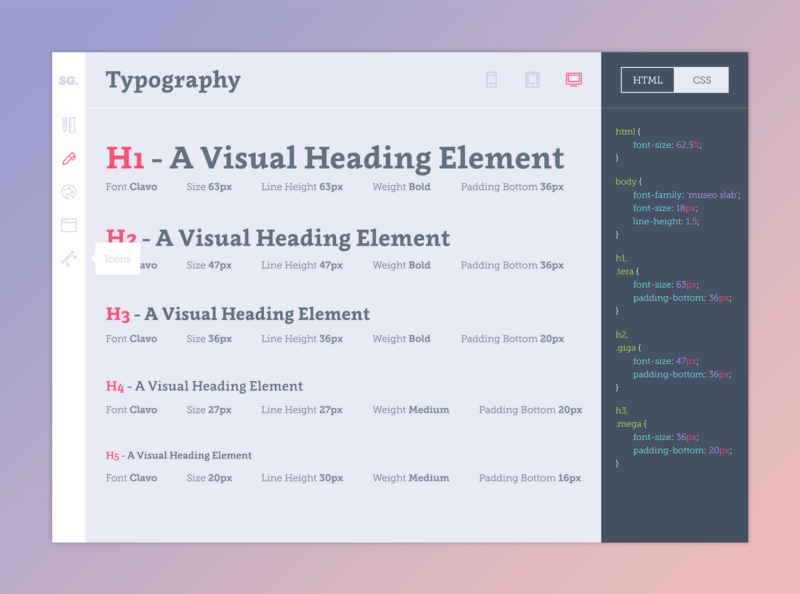
Будем считать, что художественный вкус дизайнера в рамках данной статьи не обсуждается. Я — всего лишь программист, технарь, придаток машины, да что же я понимаю в Прекрасном? Разве могу я указывать дизайнеру как Творить? Конечно же нет.
Долгое время на веб-страницах в Интернете можно было использовать только ограниченное количество шрифтов, которые встроены в операционную систему, так называемые web-safe-шрифты. Но несколько лет назад появилась директива @font-face, позволяющая встроить в страницу любой шрифт. Конечно же, дизайнеры обрадовались этой новости. Ещё бы, ведь у них появилась дополнительная возможность приблизить вид веб-страницы к её идеалу!
Но мечты о Прекрасном могут разбиться об стену Реализации, если не задумываться о ней заранее. В результате то, что видит пользователь в своём браузере может значительно отличаться (как правило, в худшую сторону) от того, что дизайнер видит у себя в Фотошопе.
Для начала, если вы вдруг не осведомлены, рекомендую прочитать статью о хинтинге — то есть о том, как шрифты отображаются на экране компьютера, и каковы различия в отображении в разных браузерах и операционных системах.
Итак, что же должен знать и делать дизайнер при выборе шрифта для дизайна сайта, чтобы конечный результат не пёрнул в лужу?
Набор символов
Думаю, это очевидно, но для порядку всё же напомню: далеко не во всех шрифтах есть кириллица (“русские буквы”). Поэтому при выборе шрифта стоит поинтересоваться, есть ли в нём кириллические символы. И в Фотошопе набирать рыбу не Lorem Ipsum, а какой-то русский текст, потому что даже если кириллица в шрифте и есть, её качество может быть ниже, чем латиницы. Набрав в качестве рыбы русский текст, вы дополнительно это проконтролируете.
Кроме того создатели шрифта могут “схалтурить” на символах, не являющихся буквами. Например, могут отсутствовать (или отвратительно выглядеть) знаки копирайта, торговой марки, знаки валют и т.д.. Особенно это относится к декоративным шрифтам, которые вполне могут содержать только буквы с цифрами и всё. Также бывают шрифты, содержащие в себе только прописные буквы и не имеющие строчных. Если вам в заголовках нужны какие-то знаки помимо букв — убедитесь, чтобы они были. Для абзацев наличие прописных и строчных букв, цифр, знаков препинания и т.д. — обязательно. Лучше использовать рыбу, содержащую все интересующие вас знаки.
Количество шрифтов на сайте и их параметров на странице
Чтобы вставить шрифт на страницу, его сперва надо сконвертировать в понятный для браузеров формат.
Если вы в своём дизайне использовали десять разных нестандартных шрифтов без веской на то причины, верстальщик вам спасибо не скажет. Во-первых, всё это добро ему предстоит встраивать, во-вторых, при вёрстке каждого элемента, помимо всего прочего, ему придётся сверяться с фотошопом, чтобы узнать, какой именно там шрифт.
То же можно сказать о размере, цвете и межстрочном расстоянии. Примите за правило, что, например, в блоках с основным текстом цвет — тёмно-серый, размер 16, межстрочное 22. В заголовках размер 36, цвет чёрный. Будет просто прекрасно, если вы, помимо PSD-файлов, на словах передадите это верстальщику. Тогда будет можно один раз и для всех страниц записать правила для такого типа элементов.
Это не говоря о том, что дизайн, где вроде бы одинаковые элементы выглядят в разных местах чуть по-разному, выглядит сам по себе неряшливо. И вместо того, чтобы сделать единый набор правил css для всех однотипных элементов, верстальщик вынужден сверять параметры и писать правила для каждого блока, что также увеличит количество матюков в ваш адрес, потому что это увеличивает его работу в разы. В худшем случае при вёрстке дизайн придётся упрощать для экономии времени. В итоге пользователь у себя на экране увидит совсем не то, что приготовил для него дизайнер.
Нет, ну конечно, если вы считаете, что на одной странице нужно делать текст цвета #222, на второй в таком же блоке #333, а на третьей снова #222, но разрядка не 22, а 23, потому что такова ваша гениальная дизайнерская задумка, и вы настаиваете, чтобы это было именно так, а верстальщик просто не хочет работать, то так тому и быть!
Но усложнение вёрстки приводит к увеличению времени, которое верстальщик затратит на работу, иногда в разы, если дизайн сделан очень безалаберно.
Отображение
Абзац
Начнём с того, что надо с особой тщательностью относиться к выбору шрифтов для абзацев. Под “шрифтом для абзацев” я понимаю шрифт, которым будут отображаться все мелкие надписи (текст в абзацах, циферки в счётчиках, копирайт в футере и всё остальное, что мелко). Здесь обязательно нужен шрифт с хинтингом, иначе получим запредельный нечитаемый трындец.
Чем мельче надпись, тем выше шанс охренеть от результата.
К сожалению, выбор-то тут весьма невелик. Качественных шрифтов с хинтингом в принципе мало (потому что делать их сложно, дорого и не окупается), а кириллические среди них — вообще вид из Красной Книги.
Так что придётся вам, дизайнеры, в данном случае обуздать свою шрифтовую фантазию, и выбирать из крайне ограниченного списка, тут ничего не поделаешь.